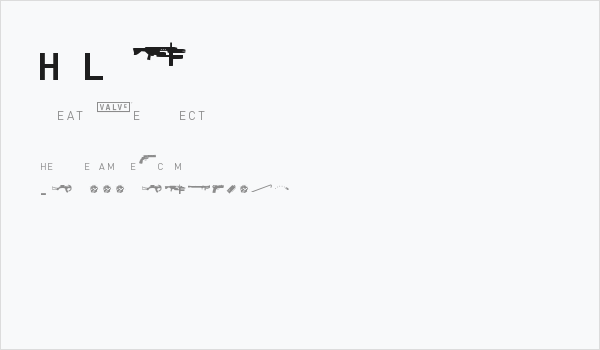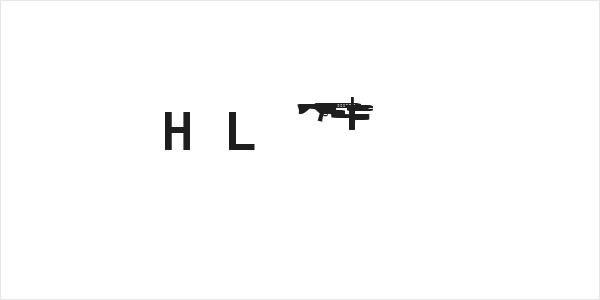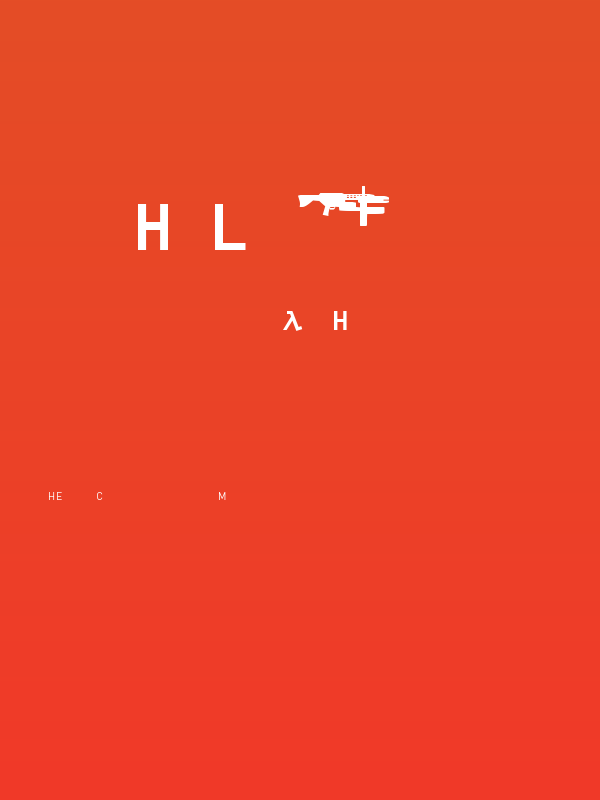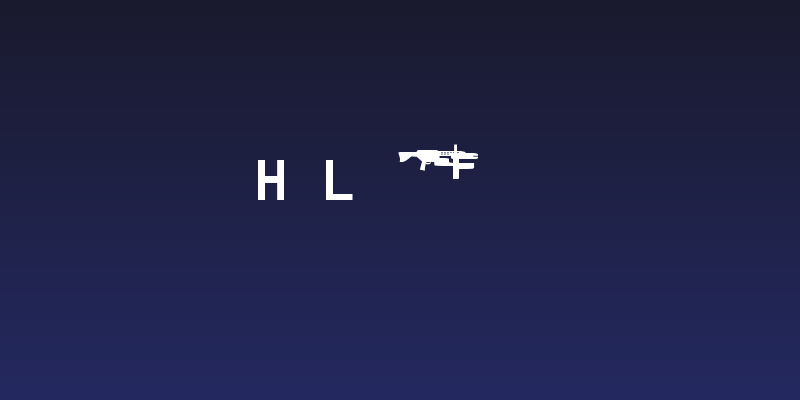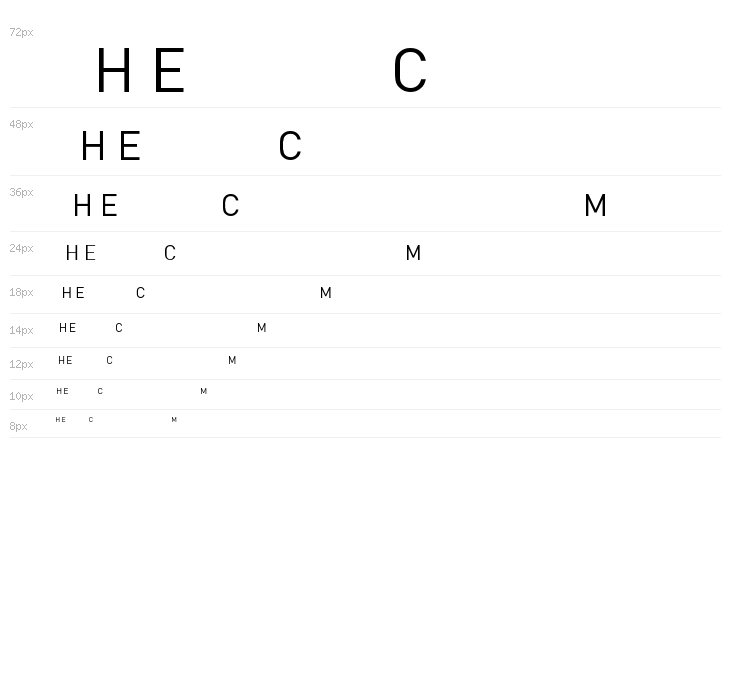
HL2MP Font
| समग्र शैली | Thematic, Game-related |
| उपयोग का मामला | Themed graphics, Merchandise design |
| सुझाए गए प्रोजेक्ट | This set of symbols could be used for themed graphic design projects, game-related artwork, or merchandise design. |